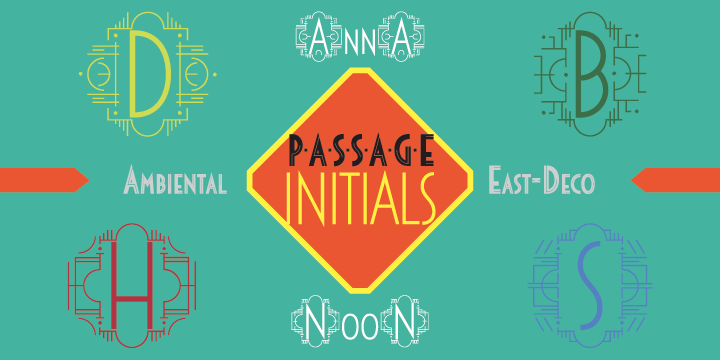
Passage™
por Tour De Force
La familia tipográfica Passage fue diseñada por Dusan Jelesijevic y publicada por Tour De Force. Passage contiene 4 estilos y opciones de paquete familiar.
Passage is freshly looking decorative Art Deco font family, inspired with modern influences.
Diseñadores: Dusan Jelesijevic
Editorial: Tour De Force
Fundición: Tour De Force
Propietario del diseño: Tour De Force